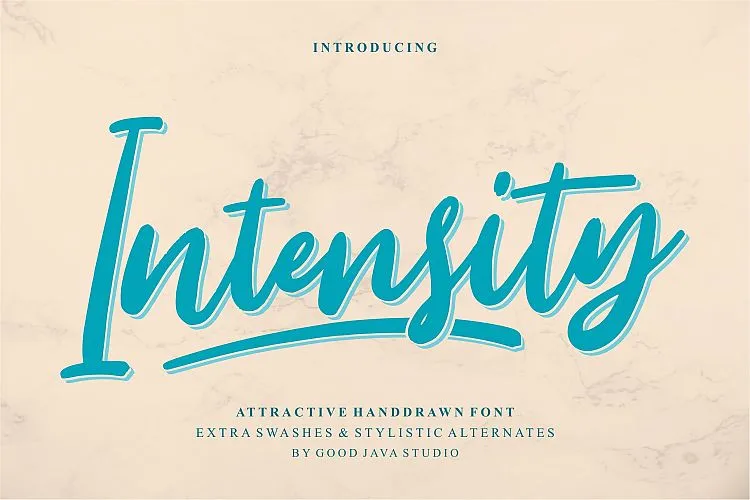
Intensity Script Font – Download Grátis
A Intensity Font é apresentada por Good Java Studio para quem busca uma fonte que seja tanto natural quanto moderna ao mesmo tempo. Esta script handwritten foi projetada com precisão, oferecendo os detalhes e personalidade característicos de um design a mão livre. Foi criada em um estilo contemporâneo que convida a usar a Intensity Font em diversos contextos — desde as mais inovadoras criações de logomarcas até embalagens exclusivas para produtos, passando por designs de casamentos e posts nas redes sociais. Suas linhas elegantes e suas paixões sutis fornecem uma opção versátil que se adapta perfeitamente a qualquer projeto. Esta fonte é perfeita para quem busca um toque único em sua identidade visual, seja ela um detalhe criativo em um cartão de convite ou um design exclusivo para embalagens de produtos de luxo. A Intensity Font também oferece uma versatilidade incrível, se adaptando com facilidade a diferentes usos e formatos. Seja você designer de marca ou pessoa que trabalha no ramo do marketing digital, o uso desta fonte pode fazer um impacto significativo em seus projetos.